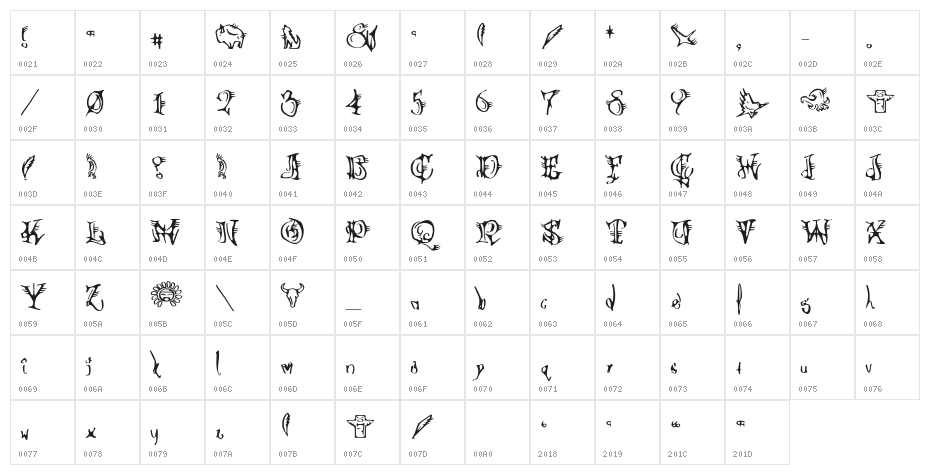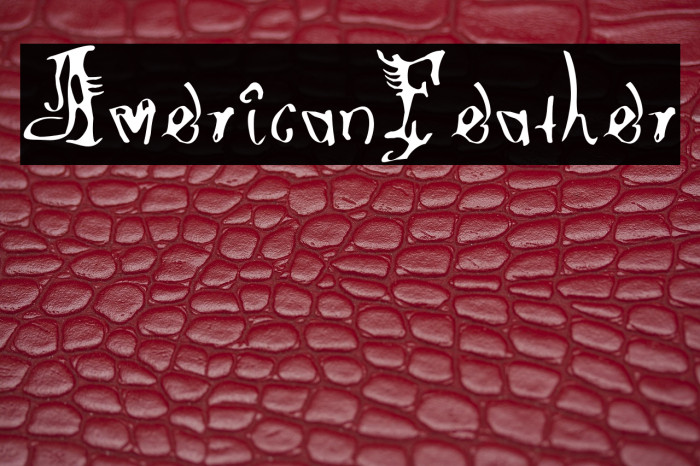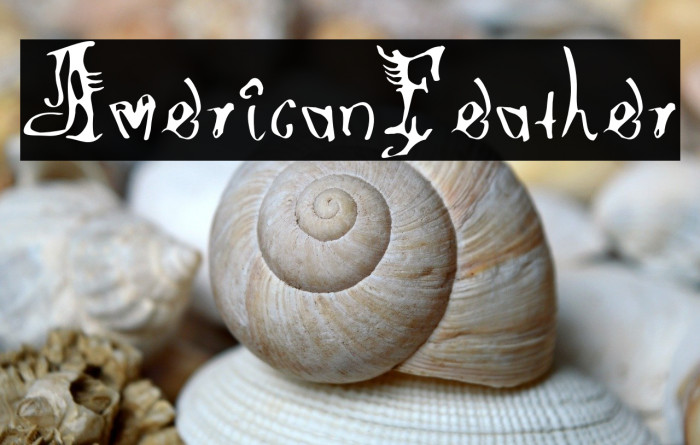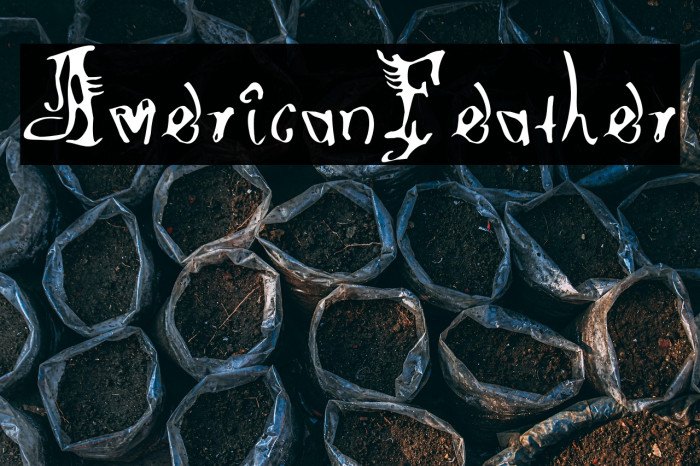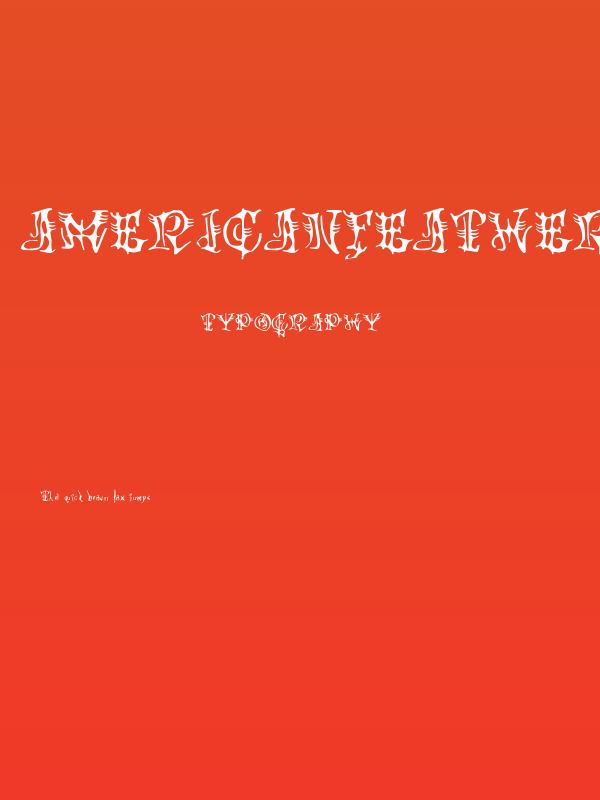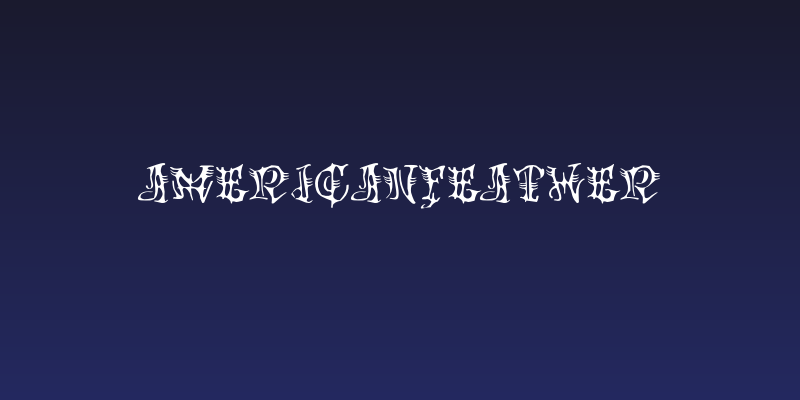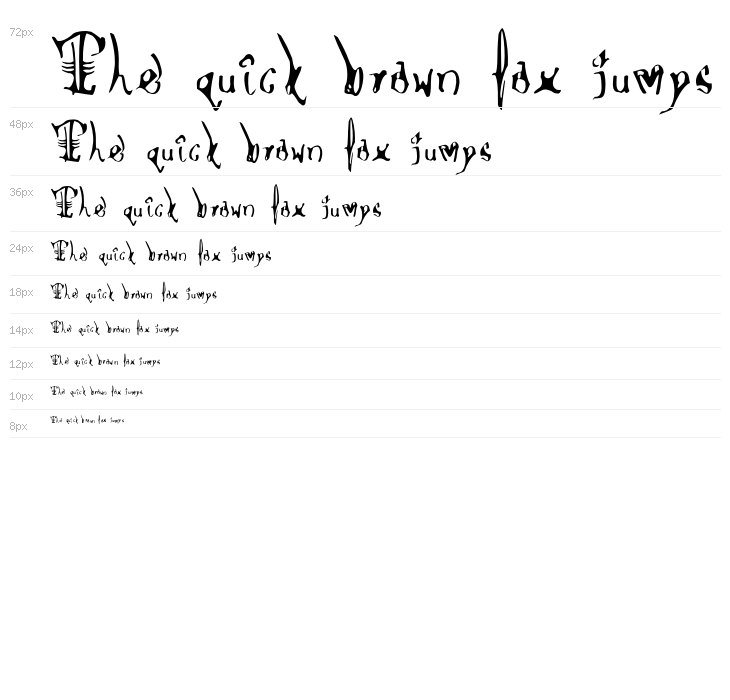
AmericanFeather Font
✎ Calligraphic
| Categorie | Calligraphic |
| Caso d'uso | Logos, Headlines, Artistic projects |
| Progetti proposti | Ideal for artistic projects, branding, logos, and invitations that require a unique and eye-catching typeface. |